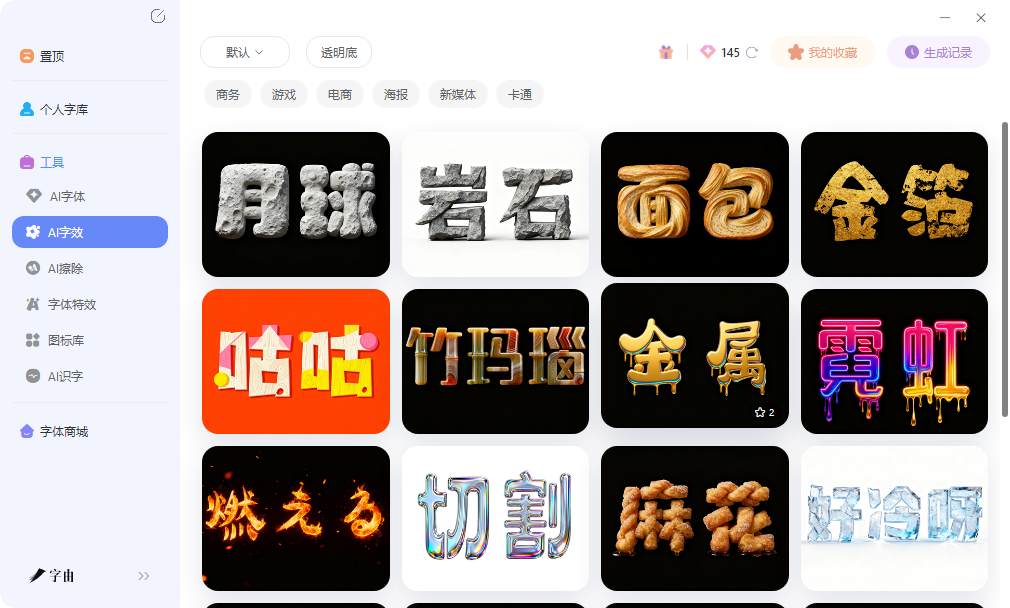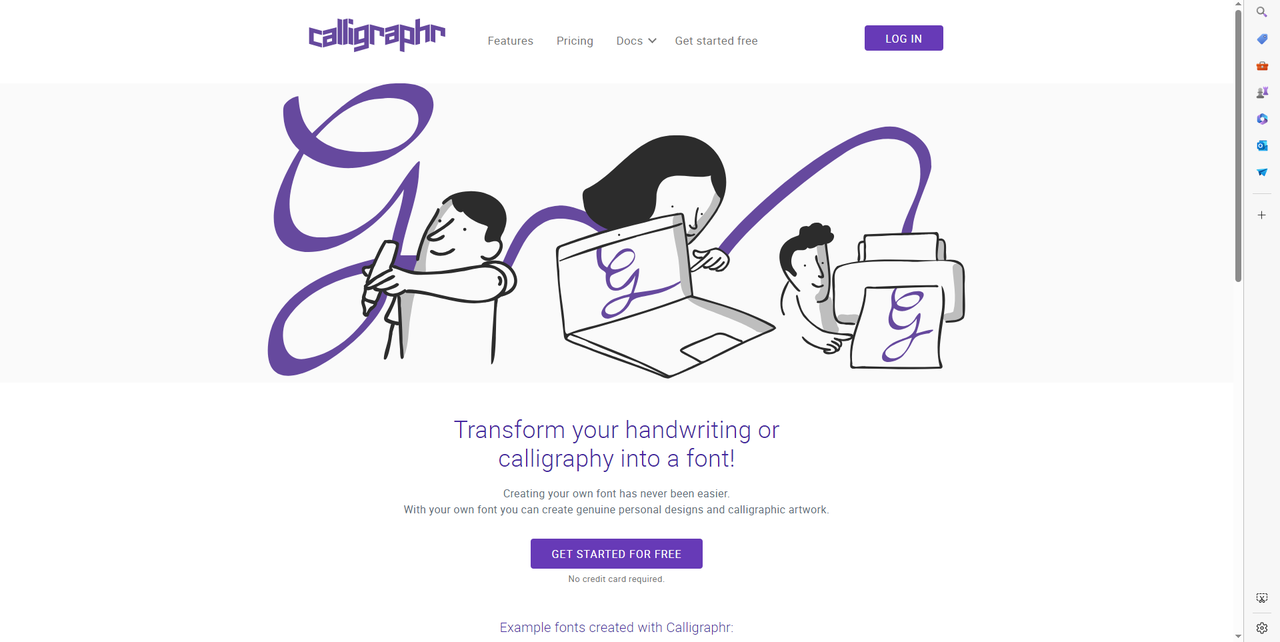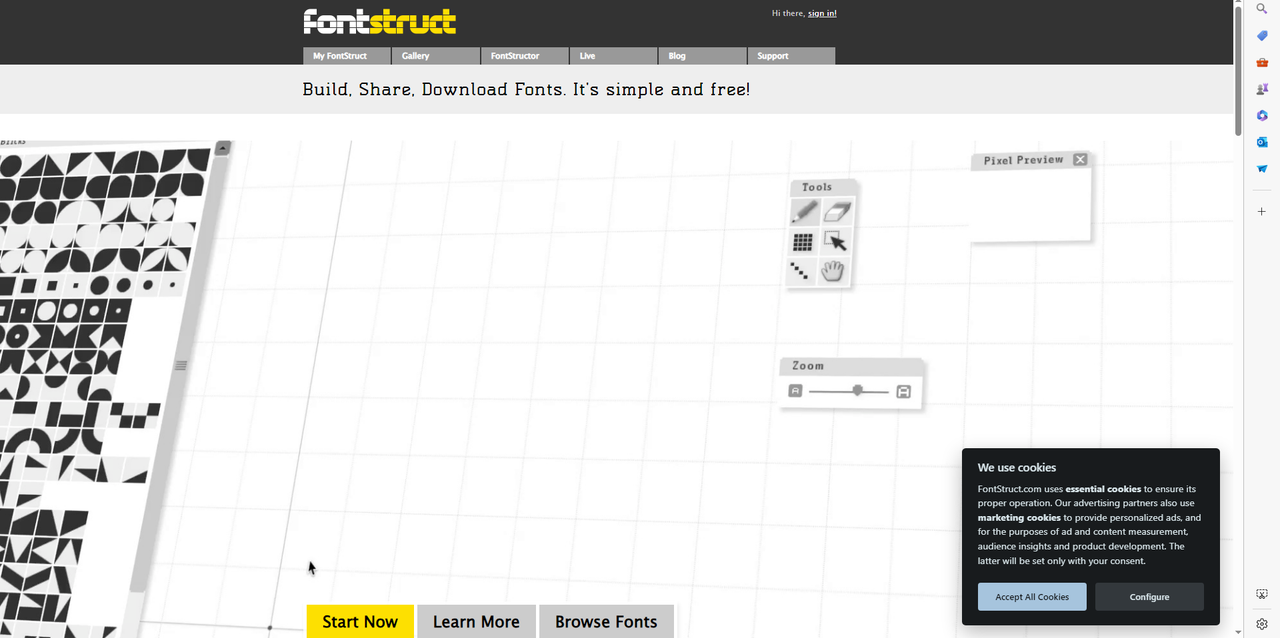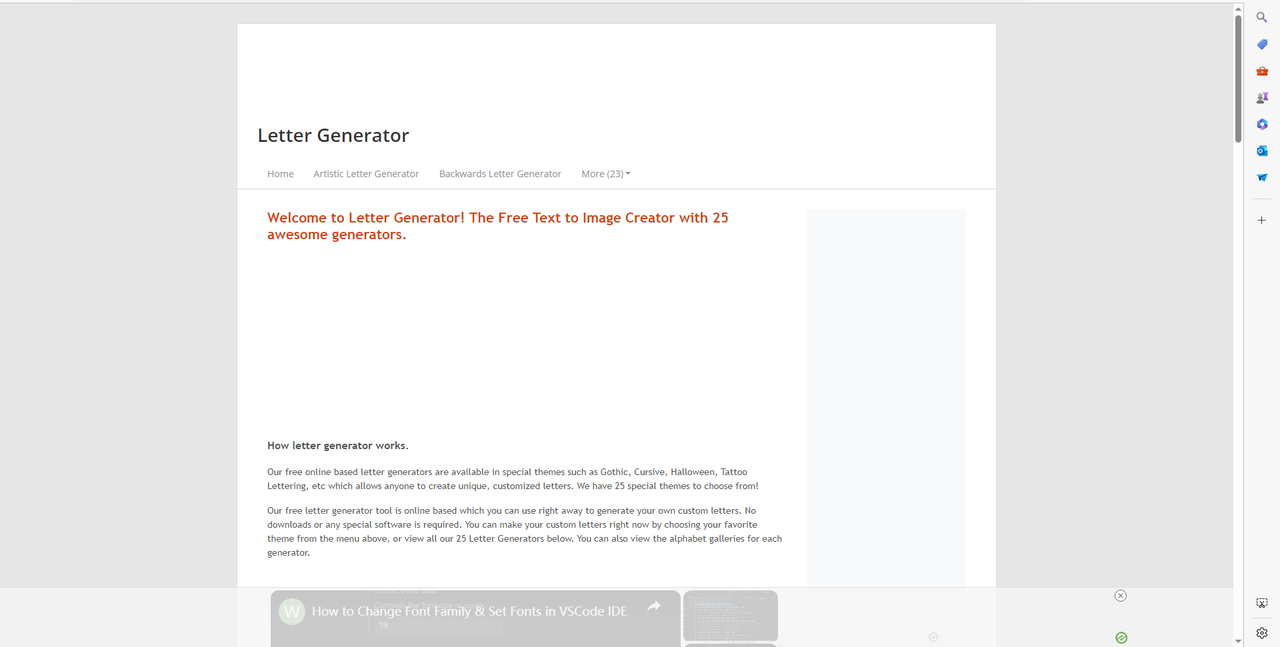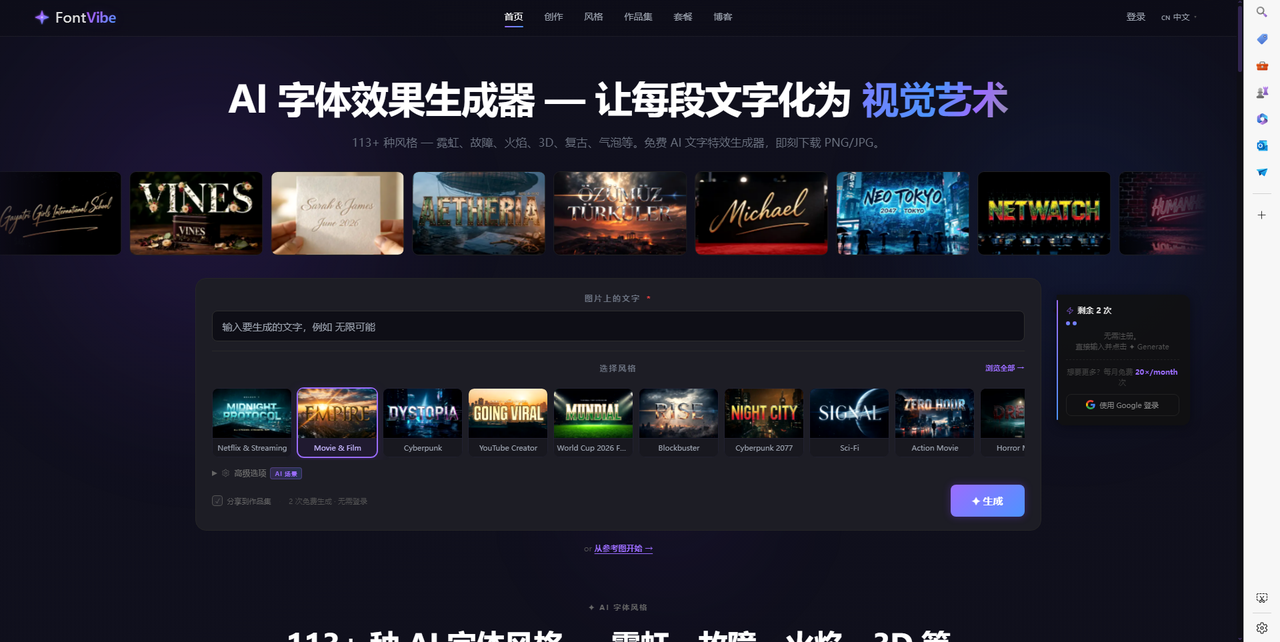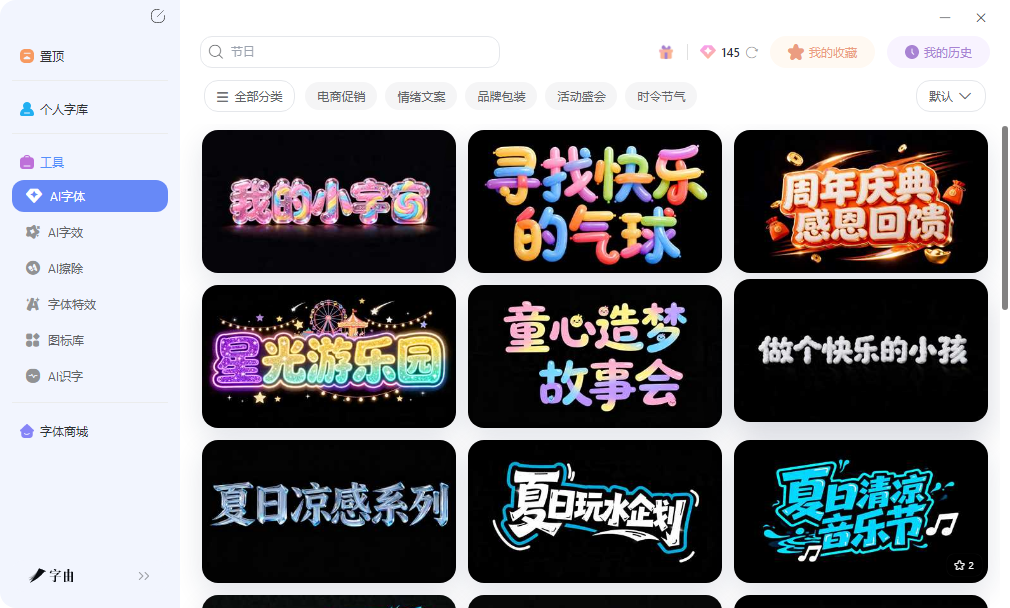
做品牌设计或者自媒体内容时,字体往往是决定整体气质的关键元素。但设计一套完整字体需要掌握字形结构、字重平衡、间距调整等专业知识,没有几年功底根本做不出来。请专业字体设计师做一套定制字体,费用动辄几万甚至几十万,对小型团队或者个人创作者来说门槛太高。其实现在有不少在线工具可以降低这个门槛,从AI自动生成风格化字体,到手写字迹数字化,再到积木式拼搭字母,打开网页就能操作。这篇文章整理的几个平台,有的用AI学习你的笔迹生成完整字库,有的把字母变成积木块自由拼搭,有的则专注风格渲染,基本能覆盖从个人创作到商业项目的字体设计需求。
字由的AI字体功能值得专门说。这个功能不是简单给文字加个滤镜,而是基于深度学习模型,根据你上传的手写样本或者选择的风格参考,生成一套完整的字体风格渲染图。AI字效则是另一个实用功能。输入文案后选择特效类型,霓虹、金属、浮雕、投影等方向都有覆盖,每种效果下还有细分变体。
遇到不确定用哪种风格的情况,可以借助AI配字功能上传参考图,系统会分析画面气质并推荐视觉上匹配的字体选项,省去反复试用的麻烦。比如上传一张国潮风海报,系统会优先推荐书法体和粗黑体;上传日系清新风格,则会推手写体或圆体,匹配效率比人工翻页找高不少。匹配结果会列出字体名称和预览图,点击就能直接激活试用,整个流程从上传参考图到确定字体只需要一两分钟
对于长期做设计的人来说,字由的价值在于把选字体、试字体、出特效图串成了一条线,不需要在多个网站之间来回跳转,工作流比较紧凑。
2、Calligraphr
Calligraphr专注把手写字迹转换成可用字体文件。下载网站提供的模板PDF,用钢笔或者毛笔在模板上写下所有字符,拍照或者扫描后上传,系统会提取笔画轮廓,生成TTF或者OTF字体文件。转换后的字体保留了手写痕迹,笔画粗细变化和连笔特征都能还原,比单纯的手写体字体更有个人特色。
这个工具对想做个人品牌、写电子手账或者做个性化文案的人来说很实用。自己的字迹变成电脑字体后,在Word、PS或者网页里都能用,既保持了手写温度,又享受了数字化排版的便利。免费版可以生成基础字符集,付费版支持更多字符和高级调节选项。对于字迹比较工整、想把手写风格融入设计项目的人来说,Calligraphr的转换精度和易用性都不错。
3、FontStruct
FontStruct走的是积木式字体构建路线。网站上提供了一个网格画布,每个格子代表一个像素,用不同形状的积木块在网格上拼出字母轮廓。积木块有正方形、圆形、三角形等基础几何形状,也有组合形状,拼搭方式和乐高类似。拼完一个字母后,系统会自动生成整套字符集,包括大小写字母、数字和常用符号。
这个工具对想做像素风、几何风或者复古8-bit风格字体的设计师很友好。传统字体设计软件学习曲线陡峭,FontStruct的积木拼搭方式直观得多,不需要懂贝塞尔曲线或者字重计算,拖拖拽拽就能做出一套风格统一的字体。生成后可以下载TTF字体文件,安装到系统里在任何软件里使用。网站上还有社区作品库,可以看到别人拼的字体,下载下来修改或者直接使用,对新手来说是很好的学习资源。
4、Letter Generator
Letter Generator的定位比较特别,它不是生成完整字体文件,而是帮你设计和装饰单个字母。输入一个字母后,系统提供几十种装饰模板,包括花卉缠绕、几何拼接、动物造型、建筑轮廓等创意方向。选择模板后可以调整颜色、纹理和细节密度,生成高分辨率的PNG图片。
这个工具对做首字母Logo、花体字标题或者个性化头像很有帮助。比如做婚礼请柬,用大写首字母加上花卉装饰,效果比用普通字体精致得多。做儿童读物封面,把字母变成动物造型,视觉吸引力明显更强。网站支持下载透明背景的PNG,直接放进设计稿里就能用。对于需要单个字母有特殊视觉效果、而不是整套字体统一风格的项目来说,Letter Generator的针对性很强。
5、FontVibe
FontVibe是一个基于AI的字体风格生成平台,核心功能是把你输入的文字转换成各种视觉风格。进入网站后输入文案,选择风格方向,比如复古印刷、未来科技、手写涂鸦、几何切割等,系统会实时生成多套方案。每套方案都有细微差别,有的笔画更粗,有的间距更紧,有的加了装饰性衬线,可以横向对比挑出最满意的那一款。
这个工具对做品牌提案的设计师很实用。给客户做Logo或者包装方案时,通常需要准备多种字体方向供选择,FontVibe可以在几分钟内生成十几种风格变体,比手动在字体库里翻找快得多。生成结果可以下载PNG图片,也可以直接复制文字样式粘贴到设计稿里。网站还提供了颜色搭配建议,根据字体风格推荐协调的配色方案,省去了自己试色的时间。对于需要快速出概念稿、验证风格方向的项目来说,FontVibe的批量生成能力很省时间。
在线工具降低了字体设计的门槛,FontVibe适合快速风格探索,Letter Generator专注单个字母装饰,FontStruct用积木拼搭做几何字体,Calligraphr把手写变成可用字库。字由在字体管理和AI特效方面提供了更系统的支持,从选字体到出特效图都能在客户端内完成。按自己的使用频率和项目类型来选,偶尔做几张图用网页工具足够,长期做设计可以搭配字由的字体库一起用,工作效率会更高。